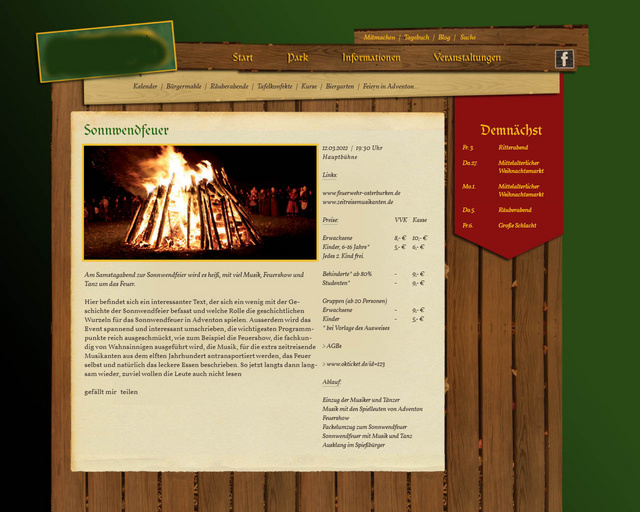
Schriftmischung Fraktur
Ich arbeite an einer Webseite für ein Mittelalter-Museumspark und möchte die Überschriften in einer Frakturschrift (Clairvaux) halten, weil diese Schrift bereits vom Park verwendet wird. Jetzt wüsste ich gerne, ob es irgendwo ausführliche Informationen über Fraktur-Schriftmischung gibt. Meist beschäftigen sich Artikel über diese Thema mit der Frage, wie das früher gemacht wurde (Zum Beispiel Auszeichnung durch Antiqua), ich möchte dagegen nur wissen, was richtig oder falsch aussieht.
Zur Zeit experimentiere ich mit der Sorts Mill Goudy oder der PT Serif in italic. Meiner Ansicht nach sieht das in Ordnung aus, allerdings ist mir bewusst, dass das etwas merkwürdig ist, also irre ich mich vielleicht.
Kann mir jemand bei dem Thema weiterhelfen?
Bei Schriftmischung sollte man ja immer auf eine gewisse Verwandtschaft mit genügender Unterscheidbarkeit achten, oder einen ganz bewusst großen Kontrast erzeugen – egal, ob mit Fraktur (gebrochenen Schriften) oder Antiqua.
Die PT Serif wirkt mir hier zu willkürlich, wenn man da einen Bruch alt/modern schaffen will, würde ich den deutlicher machen.
Die Sorts Mill passt m. E. ganz gut, wirkt dann aber eher historisierend*.
Da muss du jetzt eben gucken in welche Richtung du gehen willst.
* das ist natürlich meine eigene Meinung, nach dem ich die Schriften einzeln am Bildschirm gesehen habe. Man müsste das Zusammenspiel mal ausprobieren unter Berücksichtigung der restlichen Elemente.
Die Clairvaux ist deutlich eher eine Rundgotisch als eine Fraktur.
Kommt mir das nur so vor, oder ist das Hinting der Sorts Mill kaputt bzw. nicht vorhanden (gerade für eine Website ist das ja relevant) und einige Großbuchstaben zu hoch angeordnet (z. B. das G)?
@Schnitzel: Einen Bruch alt/modern wollte ich eigentlich nicht direkt, sonst hätte ich einfach eine Sans genommen. Aber auch keine altertümelei. Etwas passendes, aber lesbares, nicht unmodernes. Die PT habe ich auch willkürlich ausgewählt, wollte es mal probieren. Fands nicht falsch. Die Goudy macht mir ein wenig Sorgen, weil ich eben nicht historisch aussehen will. Habe vorhin noch die Tinos entdeckt, die wäre vielleicht was. Aber eigentlich suche ich hier auch keine endgültige Lösung, eher ein paar Tips, worauf ich achten soll. Zum Beispiel passen zu gebrochenen Schriftarten ja keine Schreibschriften. Schreibschrift und italic sind sich ähnlich. Ist Rotunda und italic dann tabu?
@Wrzprmpft: Das weiß ich nicht, habe sie noch nie im Web eingebettet. Ist aber eine der meistbenutzen Webfonts, also nehme ich an, dass das dann schon passt. Bei mir in InDesign siehts zumindest astrein aus. Das Hinting in der Googlefonts-Vorschau ist öfter mal komisch.
Und was die Fraktur angeht war ich etwas pauschal, ja. Ich hatte mir auch erhofft, dass jemand eine Quelle für Umgang mit gebrochenen Schriften allgemein kennt, die auf das Thema Schriftmischung eingeht. Und die werden im Volksmund oft unter Fraktur zusammengefasst.
... Rundgotisch als eine Fraktur ...
Ich denke mal, man hat sich eher an einer gotischen Minuskel orientiert, auf jeden Fall gotisch und daher thematisch/historisch passend, im Gegensatz zu einer ›echten‹ Fraktur.
Ist Rotunda und italic dann tabu?
Von einem Tabu würde ich so gut wie nie sprechen. Es kommt eben darauf an, welche Rotunda mit welcher Italic. Erstmal würde ich schon sagen, dass es ein Stilbruch ist, das kann aber auch gut wirken. Wie gesagt es kommt auch auf die Gesamtgestaltung etc. an.
Wenn du schon so eine sehr ausgeprägte (Zier-)Schrift wie die Clairvaux hast, würde ich als zweite Schrift für Texte etc. eine eher zurückgenommene ›einfache‹ Antiqua nehmen – vielleicht nicht gerade eine Garamond, aber evtl. Arno, Minion ...
Habe jetzt die Vollkorn verwendet. Die ist ein bisschen düster, aber mit einer helleren Schriftfarbe gehts. Was haltet ihr davon?
Ich habe auch beschlossen, einen zweiten Entwurf anzubieten, der moderner ist. Ich dachte, der Fließtext könnte eine Sans sein und der erste Absatz in Serif italic (Das sieht man öfter mal, hat das eigentlich einen Namen?). Ich bin aber wieder etwas ratlos bei der Auswahl. Da ich einen weiteren Schriftmix vermeiden will (Dazu verstehe ich davon zu wenig), will ich mich an eine Sippe halten. Habe es jetzt mal mit der Droid versucht. Das ist aber wieder so eine willkürliche Entscheidung. Sieht meines Erachtens zumindest nicht falsch aus.
Habe jetzt die Vollkorn verwendet. Die ist ein bisschen düster, aber mit einer helleren Schriftfarbe gehts. Was haltet ihr davon?
Kann man, wie gesagt, erst sagen, wenn man was sieht 8-)
... der Fließtext könnte eine Sans sein und der erste Absatz in Serif italic (Das sieht man öfter mal, hat das eigentlich einen Namen?). Ich bin aber wieder etwas ratlos bei der Auswahl.
Wenn da man nicht zu viel zusammenkommt :roll:
Zwischen der Sans und der Serif sind schon zwei Gestaltungssprünge und dann noch die Gebrochene ...
Könnte evtl. klappen, wenn die beiden Schriften genug Abstand zu den Elementen mit der Clairvaux haben.
Aber warum machst du dir das so schwer?
2. Wie möchtest du das durchsetzen in einem Blog, der vom Kunden geführt wird? Selber machen wird er das sicher nicht und wenn dann nicht richtig. Und der Browser ist soweit mir bekannt ist nicht in der Lage das automatisch zu erledigen. Belehre mich eines Besseren, wenn ich mich irre.
Keine Antwort mehr? Sieht es so schlimm aus? Ich bin etwas verunsichert, bin kein Designer, zumindest kein guter. Kann man das so machen?